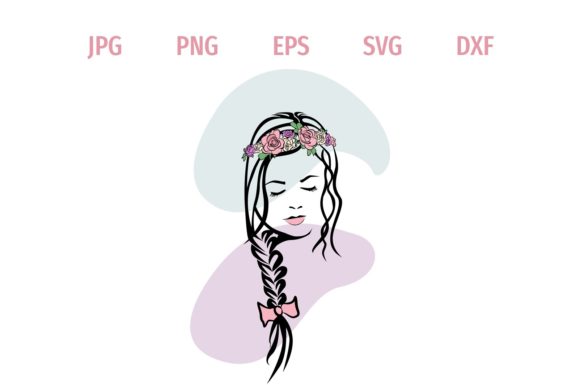
🌷 Spring Girl
Mencari elemen reka bentuk yang sesuai boleh menjadi mencabar, tetapi 🌷 Spring Girl menawarkan koleksi luar biasa yang menaik taraf karya anda serta-merta.
Sama ada anda mencipta produk POD (Print on Demand), jemputan perkahwinan atau grafik media sosial, 🌷 Spring Girl amat bersesuaian.